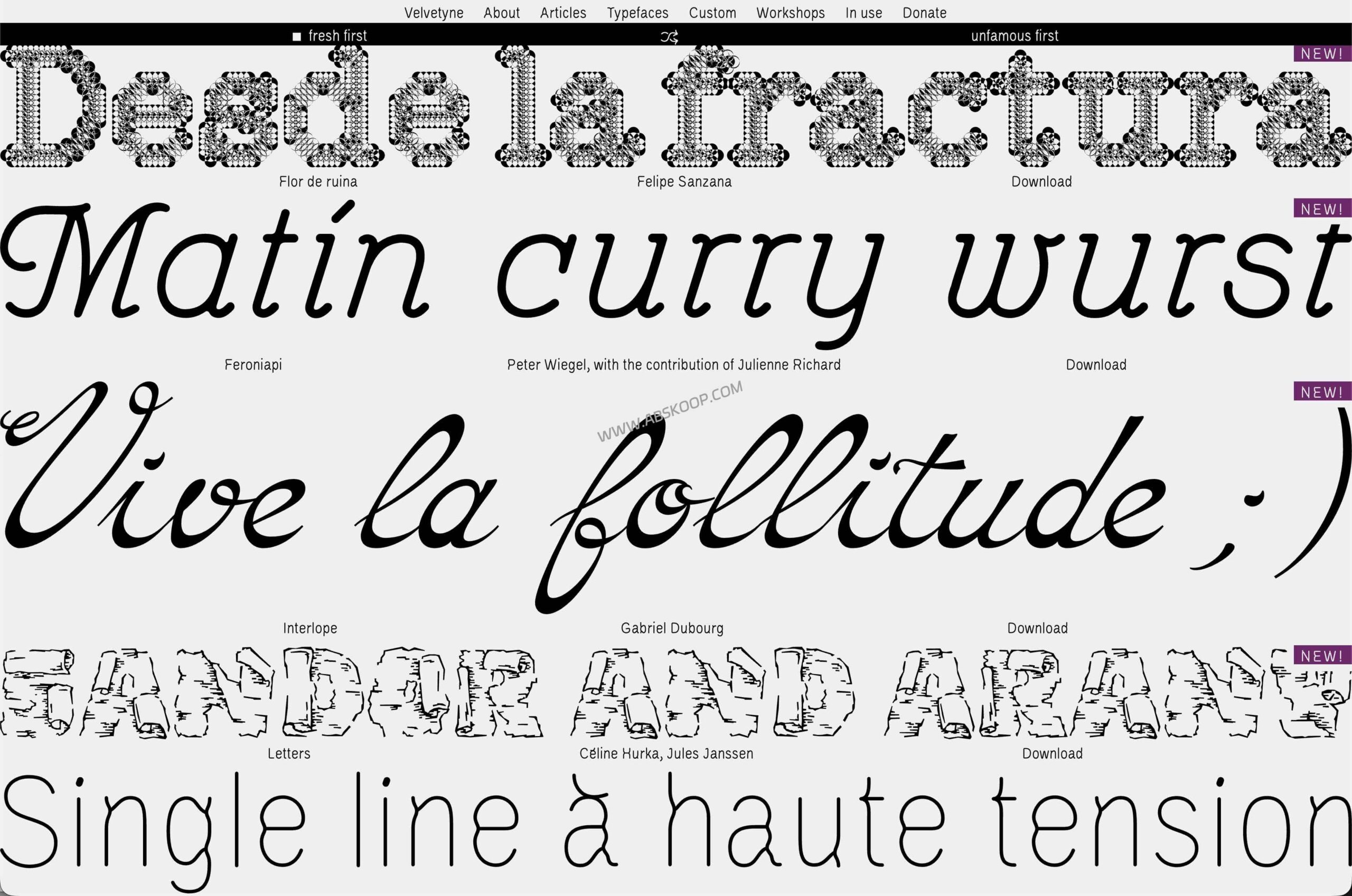
在 UI/UX 与品牌视觉高度趋同的今天,决定设计“高级感”的往往不再是工具的熟练度,而是字体的独特性。Velvetyne 正是这样一个在专业圈内口碑极高、却相对小众的宝藏资源。
它并非传统的素材下载站,而是一家来自法国的非营利开源字体铸造厂。这里的字体摒弃了平庸的通用性,充满了实验精神与前卫的艺术表达,是打造差异化商业项目、品牌视觉识别系统(VI)以及前沿 Web 设计的理想选择。
核心字体推荐与应用指南
Velvetyne 的字体自带“性格”,建议根据项目的情绪基调进行选择:
Trickster:尖锐的视觉张力
其线条带有不规则的切割感,冲击力极强。 适用场景: 科技主题海报、数字艺术 /NFT 包装、实验性 Web 页面。在 UI 设计中,建议仅用于主标题以强化视觉重心。
Pilowlava:流动且前卫
结构如同融化的熔岩,具有强烈的潮流属性。 适用场景: 潮牌主视觉、音乐节海报、创意品牌官网的 Hero Banner,能迅速建立品牌记忆点。
Avara:厚重的几何克制
以粗犷的笔画和稳定的几何结构见长,视觉分量感十足。 适用场景: 时尚杂志排版、品牌宣言页、需要权威感或力量感的商业标题。
PicNic:轻盈的亲和力
融合了手写气质与连笔设计,阅读氛围轻松。 适用场景: 食品包装、文创产品、电商品牌页面,有助于拉近品牌与消费者的距离。
适用场景速查
Velvetyne 并不追求“万能”,但在以下特定领域具有统治力:
• 品牌识别 :LOGO 设计、定制化字体系统、VI 延展。
• Productos digitales Página de inicio: Una página de presentación de productos visualmente atractiva y creativa.
• Web 开发 Proyectos front-end que buscan un estilo moderno y artístico.
• 商业营销 :需要快速脱颖而出的活动推广页。